Как подобрать шрифт – Как подобрать правильный шрифт для своего дизайна
Как подобрать правильный шрифт для своего дизайна
Дизайнеры очень часто не уделяют должного внимание типографике, когда на самом деле – это очень важный аспект, от выбора которого нередко зависит качество дизайна. Шрифты так же важны для веб-сайта, как и изображения.
Типографика – это не просто выбор шрифта. Это также этап, на котором необходимо задумать о кернинге, трекинге и интерлиньяже. Частью типографики также является выбор цвета текста, расположение текста и даже дизайн страницы.
Эффективность сообщения, которое вы хотите передать своим сайтом, часто зависит от выбора гарнитуры. Хороший шрифт завлекает зрителя и влияет на его восприятие идеи.
Хорошо подобранный шрифт помогает зрителю получать удовольствие от чтения. Необходимо всегда выбирать шрифт к подходящей ситуации.
Выбор правильной гарнитуры также усложняется тем, что доступных для использования шрифтов очень много. Нельзя сказать, что есть какое-то определенное правило, помогающее подобрать правильный шрифт во всех случаях, но есть некоторые принципы, которые могут быть использованы в самых различных ситуациях и достойны дополнительного внимания.
Разборчивость очень важна
Для того, чтобы читающий мог понимать о чем идет речь, очень важно чтобы гарнитура была разборчивой. Существует множество факторов, которые необходимо учитывать, когда дело касается разборчивости текста. Эти факторы включают в себя размер, форму и ширину символов, визуальный веc, надстроечную и подстрочную длину, а так же контрастность штриха. Выбор качественного шрифта – хорошее начало для создания разборчивого текста, но из-за огромного количества различных шрифтов выбор сделать может быть очень непросто.
Определенные элементы текста могут показаться посетителям сайта выделенными, если изменить высоту или визуальный вес шрифта. Helvetica Neue например имеет не только жирный и курсивный, но и тонкий и ультра-тонкий. Такие шрифты очень полезны, если хочется сделать дополнительный акцент на гарнитуре сайта.
Самые понятные шрифты – те буквы у которых имеют привычную форму и общее характеристики которых наиболее постоянны.
Для того чтобы шрифт казался пропорциональным приходится регулировать расстояние между символами – этот процесс называет кернингом. Таким образом улучшается вид шрифта в целом. Качественные гарнитуры всегда разбиты на керн-пары позволяющее легко достигнуть нужного эффекта. Расстояние между буквами очень влияет на разборчивость шрифта, поэтому шрифты со слишком большими расстояниями между символами стоит избегать.
Самый часто задаваемый вопрос при выборе шрифта: с засечками или без?
Самые распространение категории шрифтов – это serif или sans serif. Serif – это шрифты с заческой на концах букв. Sans serif же, соответственно – шрифты, которые засечек не имеют.
Классифицировать эти шрифты не просто, так как и тех и других шрифтов немало. В целом, serif считаются более традиционными, а sans serif – современным. Serif шрифты иногда также считаются более четкими и легкими для прочтения.
Огромное количество хороших шрифтов существует и в той, и в другой категории. Можно намного лучше начать понимать шрифты, изучая различные классификации, такие как humanist, modern, slab serif, geometric, old style и transitional. Некоторые дизайнеры даже советуют создавать свои собственные категории для удобной работы с различными проектами.
Выбираем правильный шрифт для веб–сайта и используем их правильно
Очень важно чтобы типографика привлекала зрителей и сохраняла их внимание, поэтому шрифт должны легко читаться, быть приятными и аккуратным. Заголовки и подзаголовки должны привлекать внимание, а сам контент может быть выделен определенным образом с помощью курсива, жирного шрифта цвета или положения шрифта.
Размер шрифта тоже имеет не малое значение и этим фактором не стоит пренебрегать при создании дизайна веб-страницы. Стоит отдавать предпочтение более крупному шрифту, так как его проще читать при маленьком разрешении экрана, с планшетов, смартфонов и ноутбуков.
Текст и фон также не должны сливаться. Если фон темный, то шрифт должен быть светлым и наоборот. Это гарантирует разборчивость текста и таким образом вам будет проще донести смысл текста.
Комбинирование различных гарнитур также может быть очень эффективным. Важно помнить, что шрифты должны быть достаточно различны, чтобы необходимый эффект был достигнут. Хорошим выбором будет один шрифт serif и один шрифт sans serif. Это создает контраст, который придает тексту слаженность, особенно, если это шрифты одного и того же дизайнера.
Выбор правильного шрифта для печати
Правильно подобранный шрифт поможет создать хорошее первое впечатление. Хорошо подобранная комбинация шрифтов поможет выделиться и запомниться. При этом не имеет значение печатный бланк ли это, визитная карточка или просто листовка.
Шрифт не должен перекрывать смысл текста, так как это отвлечет от информации, которую вы хотите передать. Цель гарнитуры – упростить чтение текста, и если перестараться то читатель будет смотреть только на шрифт, не воспринимая сам текст.
При распечатке необходимо также обращать внимание на контрастность и яркость, следить за тем, чтобы шрифт выглядел также как и на экране. Это поможет дизайнеру определиться с тем достигается ли необходимый эффект с помощью выбранной гарнитуры или нет.
После того как шрифт был распечатан не лишним будет показать работу знакомым. Если выбор стоит перед несколькими шрифтами, то они могут помочь определится с выбором.
Окончательное решение о том какой шрифт лучше использовать остается за дизайнером. Нет правильного или неправильного шрифта, но некоторые смотрятся на бумаге лучше, чем другие.
Ты можешь выбрать шрифт для своего сайта или печати из наших статей со шрифтами. Большинство из них бесплатные, но ты также можешь найти несколько шрифтов премиум-класса.
Вывод
Самым лучшим всегда будет считаться шрифт наиболее подходящий для конкретного случая. Это значит, что гарнитура, которая выглядит лучше всех и, допустим, занимает немного место, не обязательно станет той, которая будет выбрана. Ожидания аудитории и требования клиента должны быть всегда учтены – это также хорошее начало для многих проектов.
Основной задачей подборки гарнитуры является привлечение зрителей. Цели, которые должны быть достигнуты с помощью работы должны всегда быть четко обозначены и направлены на целевую аудиторию. Не стоит также забывать о возрастной категории и интересах аудитории.
Проекты для аудитории заинтересованной в высоких технологиях, например, имеют свои требования. Гарнитура используемая в данном случае точно будет современной: выбор может стоять между угловатыми или плавными шрифтами. Шрифты не бывают плохими или хорошими, скорее, правильно будет сказать, что они бывают подходящими и неподходящими. Гарнитура не должна быть выбрана до тех пор, пока не станет понятно, кто будет читать тест и что должно быть донесено до аудитории.
Автор статьи : Designyourway
Перевод : Sayhi
Мы рекомендуем :
20 бесплатных шрифтов, созданных в 2015 году
Микола Ковальчук: «Хороший, поганий, бридкий: Як обирати шрифт»
100 лучших бесплатных шрифтов
say-hi.me
Как выбрать шрифт — руководство для начинающих — Офтоп на vc.ru
Дизайнер и разработчик Джонатан Уайт рассказал о базовых принципах работы с типографикой.
Один из самых важных навыков для дизайнера — это умение выбирать типографику, пишет Джонатан. Ведь текст — один из основных способов коммуникации дизайнера с пользователями. И типографика может как улучшить дизайн, так и сломать его.
Типографика одновременно сложна и прекрасна. Некоторые люди посвящают ей всю свою карьеру. К счастью, их работа хорошо задокументирована, так что у нас есть множество типографических онлайн-ресурсов.
Этот материал призван сформировать начальные навыки выбора типографики для своего дизайна, а также стимулировать на эксперименты со шрифтами и их комбинациями — в том числе и неизвестными.
Определите свою цель
Прежде всего нужно понять, в чем цель вашего дизайна. Какую информацию вы хотите донести? С помощью чего? В хорошем дизайне типографика соответствует цели. Это связано с тем, что типографика — ключевой фактор в создании настроения, тона и стиля дизайна.
Например, если вы создаете дизайн приветственной карточки, который в основном полагается на изображения, лучше выбрать шрифт, который подходит к стилю иллюстраций. Шрифт должен находиться в гармонии с остальным дизайном.
Выбирайте шрифт, соответствующий стилю иллюстраций Если вы создаёте дизайн лендинга, в котором большую роль играют изображения, берите шрифт, который не будет отвлекать от иллюстраций. Шрифт в этом случае выступает как способ сделать акцент на значимой информации, несущей ключевой смысл. Если изображения — главный элемент вашего дизайна, берите простые шрифты, чтобы подчеркнуть иллюстрациюОпределите свою аудиторию
Разобравшись с целью дизайна, определитесь с аудиторией. Этот шаг крайне важен, поскольку выбор шрифтов будет зависеть от возраста, интересов и культурного бэкграунда аудитории.
Например, некоторые шрифты лучше подходят для детей. Поскольку они только учатся читать, для них лучше всего подходят легкочитаемые шрифты с крупными и различимыми буквами. Хороший пример такого шрифта — Sassoon Primary. Его создала Розмари Сассун, основываясь на собственных исследованиях того, какие буквы легче всего считываются детьми.
Sassoon PrimaryДругие шрифты лучше подходят для более взрослых детей. В таких шрифтах буквы подходящего размера, цвета — контрастные, а рукописного начертания и декоративных стилей нет.
Выбирая типографику, учитывайте аудиторию и её нужды. Проще говоря, ставьте себя на место пользователей.
Ищите вдохновение
Обратите внимание на работы других дизайнеров. Попытайтесь понять, как они определяли облик своей типографики.
Идеи для шрифтов
Если вы не знаете, какой шрифт выбрать, статья The 100 Best Free Fonts из CreativeBloq может быстро настроить вас на нужный лад. В ней автор объясняет, чем мотивирован дизайн каждого из ста представленных шрифтов.
Другой полезный источник идей — это 100 Greatest Free Fonts Collection for 2015 от Awwwards. К тому же, Invision не так давно собрали огромный список ресурсов о типографике. Там источников идей предостаточно.
Чтобы посмотреть, как идеи выглядят на реальных сайтах, зайдите на Typ.io. Там собраны примеры шрифтов со всего интернета. К тому же внизу каждого образца шрифта есть его описание в CSS.
Помимо таких сервисов «для вдохновения», обратитесь к своим любимым сайтам и посмотрите, какие шрифты они используют. WhatTheFont — неплохой инструмент для этого. WhatTheFont — это расширение для Chrome, которое позволяет изучать шрифты в вебе, проводя по ним мышкой.
Идеи для сочетаний
Помимо просто шрифтов, ищите идеи для их сочетаний. Правильные сочетания не менее важны, чем сами шрифты. Благодаря правильно подобранному сочетанию шрифтов создаётся визуальная иерархия информации и улучшается читабельность дизайна.В поисках вдохновения для сочетаний начните с Typewolf. Там собраны примеры сочетаний шрифтов с разных сайтов. Кроме того, на сайте есть рекомендации и статьи с глубоким разбором типографики. Настоящий кладезь информации.
FontPair — тоже хороший пример источника вдохновения для сочетаний шрифтов, особенно Google Fonts. Можно фильтровать комбинации стилей: например, Sans-Serif и Serif или Serif и Serif.
Выберите свои шрифты
Вдохновившись и вооружившись исследованиями, вы, наконец, готовы выбрать типографику. Когда дело доходит до этого, держите в уме следующие принципы: интересный внешний вид, разборчивость и смысл.
Прежде чем выбрать шрифт, узнайте, для чего он создавался Выбирайте шрифт, который подходит цели по общепринятым меркам и легко читается. Избегайте слишком вычурных шрифтов в пользу простых и практичных. Также помните о том, зачем вам нужен шрифт. Например, некоторые шрифты лучше подходят для заголовков, другие — для основного текста. Сочетание двух шрифтов, контрастирующих друг с другомЧто касается сочетания шрифтов, ограничьтесь максимум тремя. Кроме того, скомпонуйте их так, чтобы они контрастировали. Таким образом можно будет управлять движением взгляда читателя: сначала заголовок, потом основной текст. Также можно создавать визуальный контраст, используя разные размеры шрифтов, цвета и «вес».
Для веб-шрифтов хорошо подходят Google Fonts, Typekit, и Font Squirrel. Google Fonts бесплатны, а в Typekit и Font Squirrel есть и бесплатные, и платные шрифты.
Определите размеры шрифтов
Разобравшись с комбинациями шрифтов, займитесь их размерами. Для этого отлично подходит Modular Scale от Тима Брауна, главы отдела типографики Adobe. Фактически Modular Scale — это система для идентификации исторически сложившихся идеальных соотношений размеров шрифтов.
Например, вы можете использовать шкалу соотношений, основанную на золотом сечении. Такими будут первые пять размеров шрифтов:
Золотое сечение (1:1.618)
1.000 x 1.618 = 1.618
1.618 x 1.618 = 2.618
2.618 x 1.618 = 4.236
4.236 x 1.618 = 6.854
6.854 x 1.618 = 11.089
Значение вашего соотношения может оказаться слишком большим. Например, вот как выглядят последние интервалы в нашей шкале, основанной на золотом сечении:
Золотое сечение (1:1.618)
…
11.089 x 1.618 = 17.942
17.942 x 1.618 = 29.03
29.030 x 1.618 = 46.971
46.971 x 1.618 = 75.999
75.999 x 1.618 = 122.966
Как видите, интервалы между цифрами становятся слишком большими. Для большинства интерфейсов такие интервалы не подходят — нужно меньше. К счастью, в Modular Scale есть множество разных соотношений, основанных на принципах геометрии, природы и музыки.
Малая секунда: 15:16
Большая секунда: 8:9
Малая терция: 5:6
Большая терция: 4:5
…
Так что вместо того, чтобы использовать золотое сечение, вы можете прибегнуть к соотношениям, которые дают меньшие интервалы. Вроде чистой кварты.
Чистая кварта (3:4)
…
9.969 x 1.333 = 13.288
13.288 x 1.333 = 17.713
17.713 x 1.333 = 23.612
23.612 x 1.333 = 31.475
31.475 x 1.333 = 41.956
41.956 x 1.333 = 55.927
Определившись со шкалой размеров, вы можете выбирать отдельные размеры из списка и округлять их в сторону ближайшего целого числа.
Размеры шрифтов
Заголовок 1: 55px
Заголовок 2: 42px
Заголовок 3: 31px
Заголовок 4: 24px
Заголовок 5: 14px
Текст: 17px
Подпись: 14px
Modular Scale генерирует размеры с помощью математических формул. Однако это лишь инструмент. Пользуйтесь этим методом как основой, а затем подгоняйте размеры по своему вкусу.
Создайте типографический стайлгайд
Последний шаг процесса — создание типографического стайлгайда, чтобы стандартизировать типографику в разных ваших дизайнах.
SketchВ программах вроде Sketch вы можете создавать общие стили текстов, чтобы быстро вставлять их, руководствуясь общей идеей проекта. Именно на этом этапе нужно вносить финальные правки в типографические показатели вроде цвета, «веса» и размера.
Что касается цвета: при его выборе учитывайте свою палитру и выбирайте тон, который хорошо с ней гармонирует.
Создавая стайлгайд, убедитесь, что в нём есть как минимум такие пункты: названия шрифтов, их размеры, цвета и примеры использования. Типографические гайдлайны Material Design компании Google — хороший пример того, что должно быть в стайлгайде. По ссылкам ещё пара примеров от Mailchimp, Apple и Focus Labs.
#Интерфейсы
vc.ru
Как правильно выбрать шрифт
Выбор шрифта — непростое занятие. Красота и сложность шрифта, в сочетании с неисчерпаемым запасом вариантов, которые вам предстоит отобрать, могут вскружить вам голову. Но не отчаивайтесь. Хотя не существует простых правил по выбору лучшего шрифта, есть много проверенных на практике принципов, которые вы можете применять при выборе шрифта. Если вы постоянно будете использовать ниже предложенные советы, вы всегда сможете выбрать лучший шрифт в кратчайшие сроки. Итак, давайте начнем.
Какова ваша цель?
Первое, что вам нужно сделать для того, чтобы выбрать шрифт — в уме сформировать четкое представление о том, какую реакцию читателей на шрифт вы хотите получить. Это ваша цель, и она будет определять весь процесс. Вы можете сами придумать это впечатление, или оно может быть продиктовано вам вашим заказчиком, или вашей аудиторией. В любом случае, ваш выбор шрифта должен представлять собой отличное сочетание четкости и читабельности, оставаясь при этом подходящим для аудитории и сообщения. Каждая из этих характеристик требует отдельного рассмотрения. Как вы уже знаете из опыта, можно заострить свое внимание на чем-то ненужном, и загрузиться выбором шрифта надолго. Эта проблема может усугубляться по мере развития проекта.
Пожалуй, самая трудная часть процесса выбора шрифта — это понимание того, какие части работы являются более субъективными, а какие части — более объективным. После чтения и понимания текста вашего заказчика, легче начать с объективных аспектов выбора шрифта. Хотя нет точного разграничения спектра субъективных и объективных критериев. Давайте начнем с двух наиболее объективных признаков — четкость и читабельность.
Четкость
На первый взгляд может показаться, что четкость и читабельность одно и то же, но это не так. Четкость относится к дизайну шрифта, например к ширине штрихов, наличию засечек, наличию нового типа элементов дизайна и т.д. При разборчивом шрифте легко отличить одну букву от другой. Например, декоративные шрифты имеют низкую четкость, потому что они в первую очередь должны бросаться в глаза, а не читаться в длину. И наоборот, шрифты, предназначенные для романов или газет имеют очень высокую четкость. Вы должны разработать конкретную общую четкость на основе функции текста.
Рассмотрим следующий пример, где левая часть текста написана Tobin Tax, декоративным шрифтом с засечками. Сравните его с тем же текстом, написанным шрифтом Sabon, классическим и четким шрифтом с засечками. Какой из этих вариантов вы предпочтете?
Советы по четкости:
- Выбирайте шрифты со стандартными буквами.
Буквы с уникальными формами, художественными деформациями, чрезмерными украшениями или другими элементами дизайна заставляют читателей сначала обрабатывать увиденное, и мешают сразу воспринимать информацию. Новизна шрифта всегда мешает восприятию текста. - Выбирайте шрифты с хорошим интервалом.
Близкое расположение букв заставляет глаза заполнять оставшееся пространство, что замедляет процесс восприятия информации. Хороший интервал между буквами позволит читателю воспринимать текст быстрее. - Выбирайте шрифты с хорошей высотой строчных знаков (x-height).
Небольшая высота высота строчных знаков уменьшает четкость некоторых букв.
Обратите внимание: высота строчных букв не должна быть «большой». Размер шрифта и ширина должны выбираться в зависимости от высоты строчных букв.
Читабельность
То, как ваш шрифт расположен, в сочетании с четкостью шрифта, и определяет уровень читабельности. Читабельность — это динамическое взаимодействие стиля, размера, межбуквенного расстояния (трекинг), расстояния между соседними строками абзаца (интерлиньяж), цвета и других характеристик, объединенных в одно общее впечатление. Они складываются в определенный типографский стиль, который обладает количественной степенью читабельности. Например, вы можете намеренно использовать стиль с низкой степенью читабельности для определенной цели передачи сообщения. Или вы можете сосредоточиться на обеспечении высокой степени читабельности, если ваше сообщение будет сложным, и вы не хотите, чтобы стиль текста препятствовал пониманию. В большинстве случаев восприятие текста будет важнее, чем стиль, так что читабельность в приоритете.
Возьмем наш предыдущий пример шрифта Sabon и изменим читабельность. Слева мы уменьшили размер шрифта, изменили межбуквенное расстояние и расстояние между соседними строками абзаца, осветлили цвет. У нас получился непригодный для чтения текст. Справа мы оставили текст неизменным для сравнения. Изменение нескольких независимых факторов, как видите, может привести к видимым результатам.
Советы по читабельности:
- Выбирайте те шрифты, которые были разработаны с той целью, которую вы преследуете (шрифты для заголовков, шрифты для основного текста и т.д.). Шрифт, предназначенный для привлечения внимания, например для заголовков или плакатов, означает, что его нельзя так же эффективно применить в качестве шрифта для основного текста, где нужно читать большое количества текста. С другой стороны, шрифт, предназначенный для длительного чтения, теряет свое воздействие в большом размере.
- Не выравнивайте текст по правому краю для получения правильных пробелов между словами. Избегайте justify-выравнивания в тексте (растягивания текста на всю строку, чтобы он выглядел более ровно по краям), — это создаёт некрасивые пробелы в тексте, которые мешают читателям правильно воспринимать текст. На данный момент в CSS нет свойства, позволяющего расставлять переносы, но вы можете использовать скрипт Hyphenator.js для правильной расстановки переносов.
- Убедитесь, что расстояние между строками больше, чем размер вашего шрифта, особенно для многострочного текста. Читателям трудно будет отслеживать строчки и не перескакивать с одной на другую, если строчки расположены слишком близко. Можно спутать строчки при переходе с одной на другую. Сколько раз вы читали одну и ту же строчку текста дважды в тексте с хорошим расстоянием между строк? Наверное, один раз — если, конечно, содержание легко понять. Не заставляйте ваших читателей работать больше, чем им нужно.
Разобравшись с двумя наиболее субъективными факторами, давайте перейдем к аспектам соответствия текста.
Аспекты соответствия
Некоторые шрифты более подходят к задаче дизайна, чем другие. Уместность вы можете оценить, изучив применение конкретного шрифта на практике, а также информацию о шрифте, например его историю и изначальную функцию. Вот четыре параметра оценки уместности шрифта:
Назначение дизайна
Очень полезно бывает принять во внимание назначение шрифта. Большинство популярных шрифтов имеют детальные обзоры, так что стоит узнать хоть что-то о шрифте, который вы выбрали. Если шрифт был предназначен для рекламных надписей, как Cooper Black, например, то он, пожалуй, вряд ли подойдет для основного текста книги. Этот пример может показаться слишком очевидным, но все же не упускайте из виду такую информацию о шрифте, который вы выбрали. Посмотреть в интернете или в книге по типографии информацию о шрифте займет у вас всего несколько секунд, зато эта информация сделает вас гораздо опытнее и умнее.
Эстетика
Ваш шрифт должен соответствовать эстетике, ожидаемой аудиторией, для которой предназначен дизайн. Например, если вы разрабатываете дизайн для банка, написание их логотипа или текста для рекламной кампании в шрифте Souvenir может показаться немного легкомысленным, а это не то качество, которое нужно ассоциировать с банкирами. А вот величественный и стабильный Bembo может быть лучшим выбором в этой ситуации. Чем больше вы соотнесете суть шрифта с вашей темой, тем лучше.
В этом примере мы создали две комбинации шрифтов. В первом случае Lithos и Souvenir создают эстетику, более подходящую для детского музея, чем для банка. Вторая комбинация из Clarendon и Bembo подходят этому случаю, как хорошо сшитый костюм — банкиру.
Советы по эстетике:
- Посмотрите на шрифт и выпишите несколько слов, с которыми этот шрифт ассоциируется, а затем сравните их с целью вашего дизайна. Сходятся ли они? Поверьте, после такого анализа вы сможете сделать правильный выбор. Если вы не уверены до конца, не используйте этот шрифт.
Настроение
Эти факторы действительно немного похожи. Настроение, например, представляет собой динамичный синтез эстетики шрифта с читабельностью, а также, конечно, со смыслом самого текста. Например, с одним шрифтом и одним текстом можно вызвать настроение волнения или паники. Прежде всего, шрифт вызывает определенную реакцию, но читабельность дизайна и текст сам по себе могут поднять сообщение на новый уровень.
В приведенном ниже примере, обратите внимание, как подразумеваемое значение фразы «расслабься» резко изменилось при изменении шрифта и читабельности. Настроение тут очень мощное, и хорошо бы было попросить кого-то из знакомых оценить текст, чтобы убедиться, что вы посылаете верный сигнал. Согласование шрифта и его читабельности с запланированной эмоциональной реакцией на сообщение — вот безошибочный рецепт успеха.
Советы по настроению:
- Представьте себе абсолютно обратную реакцию на текст, и посмотрите на свою работу с этой точки зрения. Если вы не можете придумать противоположное настроение, то может быть, вам не удалось достаточно ярко передать его. Помните, что противоположность никакого настроения — никакое настроение.
Личный выбор
Часто так бывает, что шрифт вам кажется отлично подходящим. Ваше правое полушарие уверено в этом, а ваше левое полушарие не может понять, почему.
Например, вы выбрали OCR-А для обложки альбома, хотя OCR-A был разработан специально для оптических сканеров, чтобы компьютеры могли распознавать слова с помощью программного обеспечения. Так что с того, если компьютер может прочесть этот шрифт? Если он подходит для замысла вашего проекта, и вы можете сделать все правильно, сделайте это. Просто сделайте все качественно или выберите другой шрифт.
Советы по личному выбору:
- Доверяйте своему внутреннему голосу, но всегда старайтесь просчитать в количественных характеристиках все аспекты своего выбора, чтобы защитить свое решение. Даже самый субъективный выбор можно оправдать, если будет заметно, как тщательно вы обдумывали это решение.
- Выработайте собственную шкалу оценки шрифтов. Может быть, вам поможет собственный перечень тех деталей, на которые лично вы обращаете внимание при выборе шрифта. Подумайте, можно ли посчитать эти параметры, как их можно сравнивать.
Технические характеристики
Не упускайте из виду самых очевидных вещей. Например, если в вашем проекте будет много цифр, то нужно обязательно убедиться в том, что в выбранном вами шрифте есть те цифры, которые вы будете использовать. Некоторые шрифты используют Old Style (нижний регистр цифр), а некоторые шрифты используют Lining (верхний регистр цифр).
Вам может показаться, что большое количество цифр гораздо легче прочесть, если цифры будут в верхнем регистре, потому что у них не будет подстрочных элементов, и потому что они будут смотреться ровнее. Но если вам предстоит иметь дело с очень большими, близко расположенными цифрами, то нижний регистр будет выглядеть приятнее. Опять же, обратите внимание на настроение, которое хотите передать: цифры нижнего регистра выглядят старее. Это нужно использовать в нужном контексте.
К тому же, обратите внимание на то, есть ли в шрифте все лигатуры (соединение букв) и капители (малые заглавные буквы). При большом размере шрифта отсутствие лигатур может выглядеть некрасиво. Неправильные прописные буквы тоже смотрятся странно (да и вообще в русском алфавите они смотрятся странно). Если подвести итог, то лучше использовать шрифт с полным набором букв. Если вы выберете какой-нибудь бесплатный шрифт, то можете столкнуться с отсутствием необходимых вам дополнений. Так что при выборе бесплатного шрифта убедитесь, что в нем есть именно то, что вам необходимо, и что он лицензирован.
Советы по выбору шрифта
Давайте суммируем все выше сказанное в некоторые прагматические советы по выбору шрифта. Может быть, и вы в своей работе последуете этим советам, как это сделали многие дизайнеры. Используйте опыт других.
1. Продумайте иерархию
Во-первых, составьте свое представление о содержании и типографской иерархии вашего проекта. После тщательного анализа можно понять, что вам необходимо пять гарнитур (не шрифтов, разницу между понятиями гарнитура и шрифт читайте в статье основы типографики) для различных заголовков, подзаголовков и пр. Может ли ваш шрифт обеспечить достаточно заметные изменения с выделением, курсивом и капителью? Или вам нужно использовать два разных шрифта, чтобы создать более заметное различие в иерархии? Три? Набросайте обычную схему, прежде чем начать выбор шрифтов. Рассмотрим пример плохой и хорошей иерархии, используя тот же текст. Обратите внимание на роль белого пространства в иерархии. Используйте столько уровней, сколько вам нужно, чтобы было четкое различие и ясная цель вашего выбора.
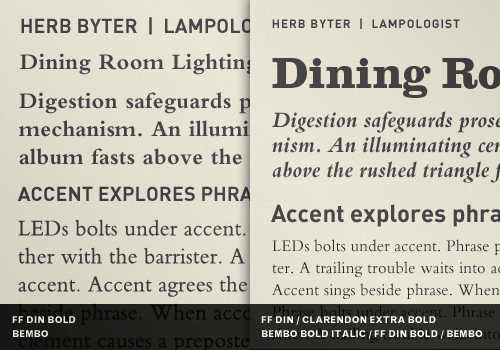
2. Учитывайте опыт других людей
Вы увидите, что дизайнеры до вас уже выработали способы использовать те же шрифты, которые хотите применить вы, так что вам не нужно изобретать колесо. Посмотрите вокруг, и внимательно изучите то, что уже сделали другие. Сайт Fonts In Use, например, содержит информацию о выборах шрифтов, сделанных профессиональными дизайнерами в различных отраслях. И не стоит пугаться, когда вы сталкивались с такими же шрифтами в работе других дизайнеров. Зачастую слова «скучный» и «знакомый» — ваши лучшие друзья, когда речь заходит о выборе типа. Существуют веские причины, по которым некоторые шрифты используются так часто- они просто работают, и работают очень хорошо.
3. Попробуйте сделать проще
Вот несколько советов, которые помогут вам экспериментировать с вариантами шрифта быстро, но вдумчиво:
- Настройте таблицы стилей и для интернета, и для печати. Это придаст мобильности, потому что их будет легко изменять. Вы можете также использовать для этой цели Web Font Specimen.
- Поиграйте с иерархией, изменяя размер различных элементов для создания и снятия напряжения.
- Оцените результаты и попробуйте что-то изменить, но изменяйте только одну вещь за раз.
- Спросите мнения независимой стороны. Возможно, вы пропустили что-то очевидное.
4. Избегайте ляпов
Например, если вы не знаете истории шрифта, то это может в конечном итоге привести вас к тому, что вы используете его таким образом, что будете выглядеть глупо. Например, вы выбрали Trajan для титульного листа статьи о Древней Греции? Это было бы неуместной неточностью, так как Греция предшествует Риму, а Траян был римским императором. Шрифт Trajan был взят с колонны Траяна, которая является памятником военной победы около 100 года нашей эры. Если вы ответите «Trajan» на вопрос «Какой шрифт вы установите на обложке этой книги о Древней Греции?», то вы будете выглядеть глупо. Все стоит проверять по несколько раз. И иногда стоит быть нейтральным, выбрав какой-нибудь безопасный шрифт для академических тем, например Arno.
5. Избегайте банальных ассоциаций
Если вы будете строго применять это правило, то вы однозначно закончите вашу карьеру с титулом почетного типографа. Давайте просто рассмотрим этот принцип на примере:
- Не используйте Papyrus, просто потому что ваша тема имеет отношение к древности, особенно к Древнему Египту. (А лучше вообще не используйте Papyrus)
- Не используйте Comic Sans только потому, что ваша тема имеет отношение к юмору. ( А лучше вообще не используйте Comic Sans)
- Не используйте Lithos только потому, что ваша тема имеет отношение к греческим ресторанам.
- Не используйте Futura только потому, что ваша тема имеет отношение к будущему.
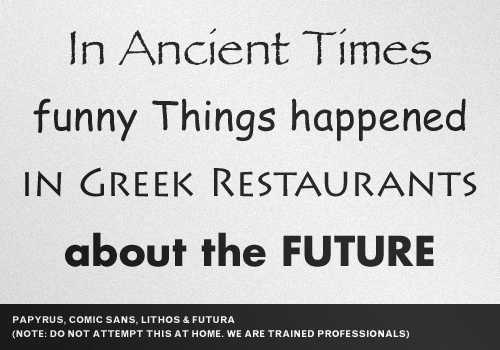
Стоит ли вообще использовать ассоциации, которые вызывают шрифты? Безусловно. Просто избегайте ассоциаций настолько очевидных, что они моментально приходят вам в голову. Признаком самых банальных ассоциаций будет являться то, что у вас есть коллекция декоративных шрифтов, которые вы часто просматриваем в вашем менеджере шрифтов, все время стараясь куда-нибудь их втиснуть. Если и вы не избежали подобных банальных ассоциаций в прошлом, не беда. Не живите прошлым, но не повторяйте ваших ошибок снова.
6. Подумайте об использовании расширенной версии шрифтов
Если ваш проект длительный и разносторонний, то было бы целесообразно рассмотреть вопрос о вложении в качественную расширенную (extended) версию шрифтов. Почему бы не поймать всех зайцев разом? Расширенные версии шрифтов, как правило, имеют версии с засечками и без засечек, наряду с несколькими видами выделения, полными наборами специальных символов и лигатур и т.д., которые гарантируют, что вы сможете найти подходящее решение практически для любого типографского задания. Расширенные группы шрифтов также позволят вам оформить все в едином настроении и эстетике, если это именно то, чего вы добиваетесь.
7. Придерживайтесь классических сочетаний
Если у вас творческий кризис, то используйте старые и проверенные шрифты, особенно если сроки поджимают. Если вы выберете сочетание нейтрального шрифта с засечками и без засечек, вы можете потерять немного «остроты» в дизайне, но, по крайней мере, целостность вашего дизайна не пострадает. Обратитесь к уважаемым ресурсам по типографии. Посмотрите, что и как делают профессиональные дизайнеры. Вполне вероятно, у вас уже есть некоторые классические примеры, на которые вы ссылались. Возможно, те же шрифты имеют полный набор всех букв и высокое качество, и использовать их вместе гораздо проще.
8. Используйте ограниченную палитру
Вы услышите много мнений по этому вопросу, но все же это не плохая идея — составить ограниченную палитру шрифтов, которые вам нравится больше всех из списка самых популярных шрифтов всех времен. Они являются наиболее популярными неспроста. Некоторые дизайнеры за время всей карьеры использовали в большинстве случаев менее двадцати шрифтов. Например, вы можете использовать FontShop’s 100 Best Typefaces (на немецком языке, также доступен в формате PDF) в качестве источника. Попытайтесь также добавить к этому списку классических шрифтов несколько новых. А также добавьте парочку уникальных, но универсальных современных шрифтов от независимых разработчиков.
В этом примере объединены Bembo и различные шрифты от Haptic Pro ( группа шрифтов, первоначально разработанной в 2008 году Henning Hartmut Skibbe). Сочетайте старое с новым, и вы сможете разработать свой уникальный стиль:
Последний совет: нарушайте правила
Нарушайте правила, но только после того, как убедитесь, что можете назвать некоторые из них. Знание основ, описанных в этой статье, поможет вам сделать осознанный выбор того, какие правила нарушать и как их нарушать. Возможно, вам придется придумать девяносто девять плохих идей, чтобы добраться, наконец, до одной отличной, но это нормально. Помните: знание шрифтов дает вам возможность выразить себя более творчески. Чтобы «выйти за границы», в первую очередь необходимо знать, где же эти самые границы.
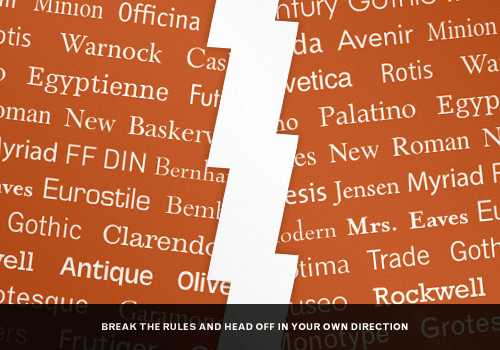
Постоянно применяя эти советы на практике, вы сможете добиться отличных результатов, которые качественно отразятся на будущих проектах.
via
Naikom » Дизайн » Типографика
naikom.ru
процесс выбора шрифта / Блог компании Everyday Tools / Хабр
Один из самых ценных навыков, которые может освоить дизайнер — это умение подбирать шрифты. Это объясняется тем, что текст является одним из основных способов коммуникации дизайнера с пользователем. Типографика имеет решающее значение для дизайна.
Типографика — вещь сложная и красивая. Некоторые посвящают работе с ней всю свою карьеру. К счастью для нас, они подробно описывают свой опыт, поэтому к нашим услугам имеется целая куча онлайн-ресурсов на тему типографики.
Эта статья замышлялась как небольшое введение для тех, кто хочет научиться правильно подбирать шрифты для дизайна. Она подтолкнёт вас к тому, чтобы расширять набор шрифтов и их сочетаний, которые вы используете в макетах, не ограничиваясь хорошо знакомыми вариантами.
Определите свою цель
Прежде всего, определите цель, которую преследует ваш дизайн. Какую информацию вы хотите передать? В каком формате?
В хороших дизайнах типографика соответствует поставленной цели. Это важно, потому что именно шрифты помогают создать определённое настроение, задают тон и стиль дизайна.
Если вы делаете, скажем, поздравительную открытку с большим количеством иллюстраций, выбирайте шрифт, который будет с сочетаться с тем стилем, в котором они выполнены. Шрифт должен гармонировать с остальными составляющими дизайна.
Если же вы проектируете вебсайт с акцентом на изображениях, выбирайте простой шрифт, который не будет отвлекать от них внимание пользователя. Используйте шрифт как способ подчеркнуть информацию, которую хотите донести.
Очертите свою аудиторию
Определившись с целью дизайна, решите, для какой аудитории вы его делаете. Этот шаг имеет огромное значение, так так сведенья о пользователях (возрасте, интересах, культурном фоне) могут оказывать влияние на решения, которые вы будете принимать при подборе шрифтов.
Например, некоторые шрифты больше подходят для младшего возраста. Детям, которые только учатся читать, нужны очень разборчивые шрифты с чёткими контурами букв. Хорошая иллюстрация к этому — Sassoon Primary. Sassoon Primary — проект Rosemary Sassoon, в основе которого лежат её исследования на тему того, какие шрифты детям проще всего считывать.
Другие шрифты более уместны для пожилых людей. Их, как правило, отличает крупный размер букв, выраженная контрастность, отсутствие прописи и декоративных элементов.
При выборе шрифта учитывайте особенности и потребности своей целевой аудитории. Говоря проще, ставьте себя на их место.
Ищите вдохновение
Посмотрите на работы других дизайнеров. Попытайтесь понять, чем они руководствовались, принимая решение использовать именно эти шрифты.
Вдохновение: шрифты
За свежими идеями насчет шрифтов можете обратиться к The 100 Best Free Fonts от CreativeBloq — это отличный источник, который придаст вам нужный настрой. В своей статье CreativeBloq объясняет логику, которой они следовали при выборе каждого из шрифтов.
Другой полезный ресурс — 100 Greatest Free Fonts Collection for 2015 от Awwwards.
Кроме того, Invision составил целый огромный репозиторий с ресурсами по типографике. Там вы найдёте массу источников для вдохновения.
Если хотите вдохновиться примером реальных веб-страниц, советую заглянуть на Typ.io. На сайте собрана коллекция источников с интересными решениями со всей Сети. Вдобавок для каждого сэмпла сайт отображает CSS-параметры шрифта под текстом.
Кроме специализированных сайтов, можете посетить свои любимые страницы и посмотреть, что используют там. Здесь вам пригодится инструмент WhatTheFont — расширение для Chrome, которое отображает информацию о шрифте, когда наведешь мышку на текст.
Вдохновение: сочетания
Помимо самих шрифтов, поизучайте разные варианты их сочетания — это не менее важно. Правильные сочетания помогают сформировать зрительную иерархию и сделать дизайн более простым для восприятия.
Первый источник для вдохновения, который стоит посетить, — это Typewolf. На Typewolf собраны примеры интересных сочетаний с разных сайтов. Также они предлагают рекомендации по подбору шрифтов и углублённые руководства по типографике. Для тех, кто работает с шрифтами, это настоящий клад.
FontPair — еще один ресурс о том, как лучше выбирать сочетания, предназначенный конкретно для работы с Google Fonts. На ресурсе предусмотрена возможность сортировки по сочетаниям стилей (например, sans-serif и serif или serif и serif).
И наконец, в Сети полно наборов готовых сочетаний от профессиональных дизайнеров. Скажем, Typography: Google Fonts Combinations или Typography: Google Fonts Combinations Volume 2. Просто вбейте запрос «font pairing» на Behance, Dribble и других подобных сайтах.
Выберите шрифт
Теперь, когда вы теоретически подкованы и запаслись вдохновением, можно приступить к выбору. В процессе отбора помните о трёх принципах: читабельность, разборчивость, цель.
Выбирайте шрифты, которые имеют классический вид и легки для восприятия. Откажитесь от вычурных шрифтов в пользу простых и практичных. И принимайте во внимание назначение того или иного шрифта: какие-то из них, допустим, больше подходят для заголовков, чем для основного текста.
Соответсвенно, прежде чем выбирать шрифт, продумайте, с какой целью будете его использовать.
Что касается сочетаний шрифтов, не делайте их слишком сложными — ограничьтесь тремя разными типами, не больше. Кроме того, подбирайте контрастирующие шрифты. Это поможет направить взгляд пользователя: сначала к заголовку, затем к основному тексту. Также создавать визуальный контраст можно при помощи разных размеров, цветов и начертаний.
Для веб-шрифтов можно использовать Google Fonts, Typekit, и Font Squirrel. На Google Fonts всё бесплатно, Typekit и Font Squirrel предлагают платные и бесплатные варианты.
Задайте размер
Теперь, когда вы определились с сочетанием, следующий шаг — выставить размеры. Для этого есть замечательный инструмент Modular Scale работы Tim Brown, главного специалиста по типографики в компании Adobe. Modular Scale — это система, определяющая соотношения, которые, как показывает история, наиболее приятны для глаза, и выстраивающая шкалу размеров текста на основании этих соотношений.
Предположим, вы выбрали шкалу на базе золотого сечения. Вот пять первых значений, которые рассчитает для вас система:
Golden Ratio (1:1.618)
1.000 x 1.618 = 1.618
1.618 x 1.618 = 2.618
2.618 x 1.618 = 4.236
4.236 x 1.618 = 6.854
6.854 x 1.618 = 11.089
Одна из проблем, с который вы можете столкнуться — это то, что с какие-то соотношения слишком велики. Смотрите, что получается, если продолжать со шкалой на базе золотого сечения:
Golden Ratio (1:1.618)
…
11.089 x 1.618 = 17.942
17.942 x 1.618 = 29.03
29.030 x 1.618 = 46.971
46.971 x 1.618 = 75.999
75.999 x 1.618 = 122.966
Как видите, разница между значениями становится слишком большой. Для большинства интерфейса нужны интервалы поменьше. Но это не страшно: на Modular Scale представлено большое разнообразие шкал — из геометрии, природы, музыки.
Minor Second 15:16
Major Second 8:9
Minor Third 5:6
Major Third 4:5
…
Поэтому вместо золотого сечения вы можете использовать другое соотношение, которое даст меньшие интервалы, например, Perfect Fourth.
Perfect Fourth (3:4)
…
9.969 x 1.333 = 13.288
13.288 x 1.333 = 17.713
17.713 x 1.333 = 23.612
23.612 x 1.333 = 31.475
31.475 x 1.333 = 41.956
41.956 x 1.333 = 55.927
Выбрав подходящую шкалу, можете надёргать размеров для разных типов шрифтов из вашего списка и округлить их до целых чисел.
Font Sizes
Header 1: 55px
Header 2: 42px
Header 3: 31px
Header 4: 24px
Header 5: 14px
Body: 17px
Caption: 14px
Метод Modular Scale предполагает расчет размер шрифтов с математической точностью, однако это всего лишь ориентир. Используйте его, чтобы получить примерные размеры, а потом подкорректируйте их на глаз.
Создайте библиотеку стилей для шрифтов
Остался последний шаг: создать библиотеку стилей, чтобы шрифты выглядели идентично во всех макетах.
В программах типа Sketch есть возможность создавать общие стили текста, чтобы быстро вставлять текст с уже заданными параметрами из таблицы стилей.
Именно на этом этапе вы должны окончательно определиться с цветами, начертаниями и размерами. Кстати о цветах: выбирайте их с оглядкой на общую палитру. Цвета текста должны гармонично с ней сочетаться.
Обязательно включите в библиотеку стилей следующее: типы шрифтов, цвета, размеры и образцы. Таблица стилей от Google’s Material Design typography— хороший пример того, как её составлять. Также как пособия можно использовать библиотеки стилей от Mailchimp, Apple, и Focus Labs.
Типографика — это область экспериментов, искусство и наука в одном флаконе. Я призываю вас выйти из зоны комфорта и активно исследовать все возможности.
habr.com
Как подобрать правильный шрифт для своего дизайна
Дизайнеры очень часто не уделяют должного внимание типографике, когда на самом деле — это очень важный аспект, от выбора которого нередко зависит качество дизайна. Шрифты так же важны для веб-сайта, как и изображения.
Типографика — это не просто выбор шрифта. Это также этап, на котором необходимо задумать о кернинге, трекинге и интерлиньяже. Частью типографики также является выбор цвета текста, расположение текста и даже дизайн страницы.
Эффективность сообщения, которое вы хотите передать своим сайтом, часто зависит от выбора гарнитуры. Хороший шрифт завлекает зрителя и влияет на его восприятие идеи.
Хорошо подобранный шрифт помогает зрителю получать удовольствие от чтения. Необходимо всегда выбирать шрифт к подходящей ситуации.
Выбор правильной гарнитуры также усложняется тем, что доступных для использования шрифтов очень много. Нельзя сказать, что есть какое-то определенное правило, помогающее подобрать правильный шрифт во всех случаях, но есть некоторые принципы, которые могут быть использованы в самых различных ситуациях и достойны дополнительного внимания.
Разборчивость очень важна
Для того, чтобы читающий мог понимать о чем идет речь, очень важно чтобы гарнитура была разборчивой. Существует множество факторов, которые необходимо учитывать, когда дело касается разборчивости текста. Эти факторы включают в себя размер, форму и ширину символов, визуальный веc, надстроечную и подстрочную длину, а так же контрастность штриха. Выбор качественного шрифта – хорошее начало для создания разборчивого текста, но из-за огромного количества различных шрифтов выбор сделать может быть очень непросто.
Определенные элементы текста могут показаться посетителям сайта выделенными, если изменить высоту или визуальный вес шрифта. Helvetica Neue например имеет не только жирный и курсивный, но и тонкий и ультра-тонкий. Такие шрифты очень полезны, если хочется сделать дополнительный акцент на гарнитуре сайта.
Самые понятные шрифты — те буквы у которых имеют привычную форму и общее характеристики которых наиболее постоянны. Для того чтобы шрифт казался пропорциональным приходится регулировать расстояние между символами – этот процесс называет кернингом. Таким образом улучшается вид шрифта в целом.
Качественные гарнитуры всегда разбиты на керн-пары позволяющее легко достигнуть нужного эффекта. Расстояние между буквами очень влияет на разборчивость шрифта, поэтому шрифты со слишком большими расстояниями между символами стоит избегать.
Самый часто задаваемый вопрос при выборе шрифта: с засечками или без?
Самые распространение категории шрифтов – это serif или sans serif. Serif – это шрифты с заческой на концах букв. Sans serif же, соответственно — шрифты, которые засечек не имеют.
Классифицировать эти шрифты не просто, так как и тех и других шрифтов немало. В целом, serif считаются более традиционными, а sans serif — современным. Serif шрифты иногда также считаются более четкими и легкими для прочтения.
Огромное количество хороших шрифтов существует и в той, и в другой категории. Можно намного лучше начать понимать шрифты, изучая различные классификации, такие как humanist, modern, slab serif, geometric, old style и transitional. Некоторые дизайнеры даже советуют создавать свои собственные категории для удобной работы с различными проектами.
Выбираем правильный шрифт для веб-сайта и используем их правильно
Очень важно чтобы типографика привлекала зрителей и сохраняла их внимание, поэтому шрифт должны легко читаться, быть приятными и аккуратным. Заголовки и подзаголовки должны привлекать внимание, а сам контент может быть выделен определенным образом с помощью курсива, жирного шрифта цвета или положения шрифта.
Размер шрифта тоже имеет не малое значение и этим фактором не стоит пренебрегать при создании дизайна веб-страницы. Стоит отдавать предпочтение более крупному шрифту, так как его проще читать при маленьком разрешении экрана, с планшетов, смартфонов и ноутбуков.
Текст и фон также не должны сливаться. Если фон темный, то шрифт должен быть светлым и наоборот. Это гарантирует разборчивость текста и таким образом вам будет проще донести смысл текста.
Комбинирование различных гарнитур также может быть очень эффективным. Важно помнить, что шрифты должны быть достаточно различны, чтобы необходимый эффект был достигнут. Хорошим выбором будет один шрифт serif и один шрифт sans serif. Это создает контраст, который придает тексту слаженность, особенно, если это шрифты одного и того же дизайнера.
Выбор правильного шрифта для печати
Правильно подобранный шрифт поможет создать хорошее первое впечатление. Хорошо подобранная комбинация шрифтов поможет выделиться и запомниться. При этом не имеет значение печатный бланк ли это, визитная карточка или просто листовка.
Шрифт не должен перекрывать смысл текста, так как это отвлечет от информации, которую вы хотите передать. Цель гарнитуры – упростить чтение текста, и если перестараться то читатель будет смотреть только на шрифт, не воспринимая сам текст.
При распечатке необходимо также обращать внимание на контрастность и яркость, следить за тем, чтобы шрифт выглядел также как и на экране. Это поможет дизайнеру определиться с тем достигается ли необходимый эффект с помощью выбранной гарнитуры или нет.
После того как шрифт был распечатан не лишним будет показать работу знакомым. Если выбор стоит перед несколькими шрифтами, то они могут помочь определится с выбором.
Окончательное решение о том какой шрифт лучше использовать остается за дизайнером. Нет правильного или неправильного шрифта, но некоторые смотрятся на бумаге лучше, чем другие.
Ты можешь выбрать шрифт для своего сайта или печати из наших статей со шрифтами. Большинство из них бесплатные, но ты также можешь найти несколько шрифтов премиум-класса.
Вывод
Самым лучшим всегда будет считаться шрифт наиболее подходящий для конкретного случая. Это значит, что гарнитура, которая выглядит лучше всех и, допустим, занимает немного место, не обязательно станет той, которая будет выбрана. Ожидания аудитории и требования клиента должны быть всегда учтены — это также хорошее начало для многих проектов.
Основной задачей подборки гарнитуры является привлечение зрителей. Цели, которые должны быть достигнуты с помощью работы должны всегда быть четко обозначены и направлены на целевую аудиторию. Не стоит также забывать о возрастной категории и интересах аудитории.
Проекты для аудитории заинтересованной в высоких технологиях, например, имеют свои требования. Гарнитура используемая в данном случае точно будет современной: выбор может стоять между угловатыми или плавными шрифтами. Шрифты не бывают плохими или хорошими, скорее, правильно будет сказать, что они бывают подходящими и неподходящими. Гарнитура не должна быть выбрана до тех пор, пока не станет понятно, кто будет читать тест и что должно быть донесено до аудитории.
Источник: say-hi.me
Фото на обложке: ShutterStock
infogra.ru
Как правильно подобрать шрифт для сайта
Создание потрясающих шрифтовых композиций – это скорее искусство, чем наука. Действительно, красота шрифтов не имеет границ. И хотя нет абсолютных правил их сочетания между собой, все же хорошо следовать лучшим практикам веб-типографики. В данной статье показаны лучшие приемы сочетания шрифтов, а также традиционные ошибки.
1. Сочетайте шрифты с засечками со шрифтами без засечек (sans serif и serif)
Самый популярный типографский прием – набор заголовка рубленым (без засечек) шрифтом, а текста – шрифтом с засечками. Это классическая комбинация, в ней почти невозможно ошибиться.
В примере ниже — типичный макет статьи, в заголовке использован Trade Gothic Bold No.2, а в тексте — Bell Gothic. Оба шрифта – рубленые, тем не менее, у них очень разные «личности». Хорошее правило при создании макета — не привлекать излишнее внимание читателя к виду шрифта. Trade Gothic предполагает серьезность, а Bell Gothic, наоборот – динамику и экспрессивность.
Сочетание этих шрифтов вызывает нежелательный дизайнерский конфликт. Trade Gothic хочет перейти прямо к фактам, а Bell Gothic хочет веселиться. Такое напряжение между шрифтами – не наша цель, его следует избегать.
Теперь рассмотрим пример справа. Bell Gothic заменён шрифтом Sabon. Sabon, как шрифт с засечками, очень хорошо работает с Trade Gothic. Они оба нацелены на ясность и читабельность благодаря хорошей высоте знаков x-height (грубо говоря, это высота строчной буквы x в шрифте, она определяет расстояние между базовой линией и верхней). Таким образом, у обоих шрифтов одна и та же цель, что создает прекрасное сочетание.
2. Избегайте шрифтов одного класса
Шрифты одного класса, но из разных семейств могут запросто вызвать разногласие при их комбинировании. Их ярко выраженные личности будут тянуть одеяло каждая на себя, в результате макет станет «грязным».
На примере внизу, слева, в заголовке использован шрифт Clarendon Bold, который относится к классу Slab serif. В теле статьи использован Officina Serif который также относится к Slab serif. Шрифты класса Slab serif отличаются ярко выраженным характером, им нравится доминировать на странице. Использование двух шрифтов класса Slab serif в одном месте может вызвать ненужное напряжение.
А теперь обратите внимание на правую сторону примера. Clarendon Bold в заголовке поставлен рядом с более нейтральным New Baskerville. New Baskerville относится к универсальному классу Transitional serif с широкими знаками, которые хорошо сочетаются с жирным Clarendon. Выбор шрифтов разных классов с самого начала избавит вас от головной боли при создании макета.
3. Присвойте шрифтам разные роли
Один из простых способов комбинации шрифтов, это составление ролевой дизайнерской схемы для каждого шрифта. В примере ниже мы использовали Akzidenz Grotesk Bold прописными для имени автора статьи. Для заголовка — Rockwell Bold. Вводный абзац и основной текст статьи в одном шрифте – Bembo, но разного размера. И, наконец, подзаголовок — Akzidenz Grotesk Medium.
Отчетливый Rockwell Bold мы оставили для привлечения внимания к заголовку. В целом использовали уже открытую нами схему сочетания рубленого шрифта и шрифта с засечками. И даже при таком выборе у нас большое количество вариаций по размеру, весу и функциям шрифтов. В общей сложности использовались 4 шрифта из 3-х гарнитур, все они привели к связанному, сплоченному дизайну, так как у каждого шрифта своя роль, четко определенная в типографической иерархии. Так что если сомневаетесь – распределите роли!
4. Контрастная насыщенность шрифтов
Самый лучший способ испортить макет – не разделить элементы текста друг от друга по их иерархии. Кроме использования разных размеров, убедитесь, что ваши шрифты разного веса (жирности), чтобы дать читателю «путеводитель» по вашему дизайну.
На примере слева у нас разные размеры шрифта, но недостаточный контраст по толщине. Myriad Light рядом с Minion Bold «пропадает» и теряет визуальный авторитет. Как бы то ни было, но глаз читателя должен в первую очередь выделять заголовок, а не превью.
Справа мы использовали Myriad Black над Minion нормальной толщины. Возможно, заголовок тяжеловат, но по крайней мере, у читателя не возникает сомнений по поводу того, что читать первым.
5. Создайте на странице различную тональность текста
В типографии тональность достигается различными способами – толщиной, размером, шириной строк, кернингом и пр. Самый простой способ «увидеть» тональность – смотреть на макет не прямо, а боковым зрением. Посмотрите на пример внизу, направив взгляд немного справа или слева от картинки, так, чтобы вы уже не могли читать текст, но могли видеть его общий тон. При таком взгляде вы заметите, что пример слева сливается в один серый блок текста, немного темнее внизу. А вот пример справа отчетливо сохраняет свою визуальную иерархию. Как бы далеко вы не находились от текста, у вас не возникает сомнений по поводу того, где находится заголовок, и куда ваш взгляд перейдет потом.
Умное использование текстовой тональности усиливает визуальную иерархию на странице, что напрямую связано с передачей смысла сообщения.
6. Не смешивайте настроения шрифтов
Одна из частых ошибок – игнорирование присущего шрифту настроения. Шрифты имеют свою личность. Иногда настроение шрифта может меняться в зависимости от контекста, но несущественно. Одна проблема – неправильно подобрать шрифт для конкретной работы. Но еще большая проблема – составить два шрифта с разным настроением!
На примере слева мы соединили Franklin Gothic Bold и Souvenir. Общее впечатление от Franklin Gothic – мужество, сила, стойкость, но с налетом элегантности. Он не ублажающий взор, но очень функциональный. А Souvenir – игривый, легкомысленный, немного равнодушный, но очень симпатичный. Сочетание этих двух шрифтов подобно встрече гвардейца, охраняющего Букингемский дворец, и девочки. Гвардеец послушно игнорирует игривую девчонку у его ног, пытающуюся заставить его улыбнуться. Такое смешение плохо работает. Разное настроение шрифтов привлекает внимание к самим шрифтам, а не содержанию, что свидетельствует о слабом дизайне.
Справа в пару к Souvenir мы поставили более подходящего соседа. У Futura Bold много лиц, но он очень хорошо сочетается с Souvenir по многим причинам. Во-первых, у обоих шрифтов высокие x-height. Оба шрифта обладают округлостью форм и незначительной, но тем не менее заметной закрученностью концов. Ни один из них не доминирует над другим. Оба работают на создание веселого, приподнятого настроения. Напряжения между ними нет.
7. Сочетайте яркое с нейтральным
Чистый, читабельные типографский дизайн требует внимательного отношения к намеренному и непреднамеренному напряжению между шрифтами. Столкновение разных личностей шрифтов – это только одна причина ненужного напряжения. Если один из шрифтов имеет яркую личность, то второй должен быть нейтральным.
На примере слева Dax Bold стоит рядом с Bernhard Modern. Это плохой выбор хотя бы по двум соображениям. Во-первых, Dax имеет узкие знаки и большую x-height, в то время как Bernhard Modern, наоборот, при большой ширине глифов обладает одной из самых низких x-height среди популярных классических гарнитур. Во-вторых, Dax неформальный, современный и яркий. Идеально подходит при подачи текста технарям, компьютерщикам и вообще современной молодежи. Bernhard Modern, наоборот, классический, спокойный, рафинированный и даже немного личный. Объедините неподходящие физические характеристики шрифта с личностными, и получите очень плохо функционирующую типографику.
Взглянем на более удачный выбор. В правой колонке Dax Bold поставили рядом с Caslon, который относится к классу Old style, но был модернизирован и смягчен для лучшей сочетаемости с другими шрифтами. В данном контексте он выглядит удовлетворительно рядом с Dax. Заметьте, как в первую очередь мы видим личность Dax в заголовке, и как Caslon отступает назад и приглашает нас к чтению. В этом примере Caslon является нейтральным выбором для поддержки более яркого Dax.
8. Избегайте несоизмеримых сочетаний
Когда между выбранными шрифтами слишком большой контраст, это создает визуальный дисбаланс, что плохо отражается на всем дизайне. Слева мы поставили Antique Olive Nord – чрезвычайно жирный шрифт, — рядом с Garamond Narrow. Контрастный перебор очевиден. В большинстве подобных случаев, такой контраст идет дальше обычного привлечения внимания и вызывает ощущение неуклюжести. Следовательно, он не доносит до читателя смысла текста.
Справа Antique Olive Nord был заменен более мягким и сдержанным Antique Olive Bold. Garamond Narrow мог бы быть заменен на тот же Garamond в варианте book weight, но более хорошим выбором нам представляется Chaparral. У Chaparral более высокая x-height, чем у Garamond, и в общем у него более современный и нейтральный вид рядом с характерным Antique Olive Bold.
9. Будьте проще – не используйте более двух шрифтов
Вместо того, чтобы перелопачивать библиотеки шрифтов в поисках «того самого» сочетания, иногда лучше вернуться к классическому и гораздо более простому варианту – сочетанию шрифта с засечками и рубленого. На примере внизу мы составили четкую типографскую иерархию, добились разнообразия, получили интересную разбивку по тональности текста и его возрастающую читабельность. Все это было сделано с помощью всего двух шрифтов. Хотя, строго говоря, у нас здесь пять шрифтов: три Helvetica Neue и два Garamond.
Как добиться всего этого без лишних усилий? Во-первых, если вы возьмете шрифты из одной и той же гарнитуры, то наверняка получите отличную визуальную совместимость даже не задумываясь над этим. Во-вторых, мы выбрали проверенную временем комбинацию – сочетание нейтрального заголовочного шрифта и опять же нейтрального шрифта для текста. И Helvetica Neue, и Garamond обладают выраженной, но нейтральной личностью, и они могут сочетаться в сложных макетах друг с другом, потому что мы изначально заложили строгую иерархию. Следование правилам при использовании правильных шрифтов помогает достичь высоких результатов без лишних затрат энергии.
10. Используйте различные размеры шрифта